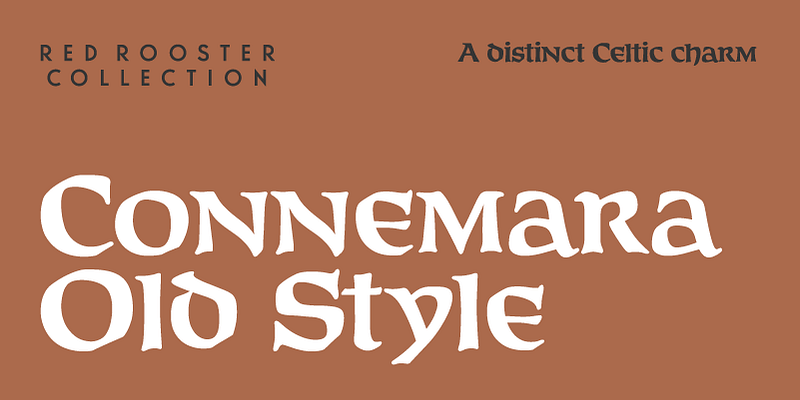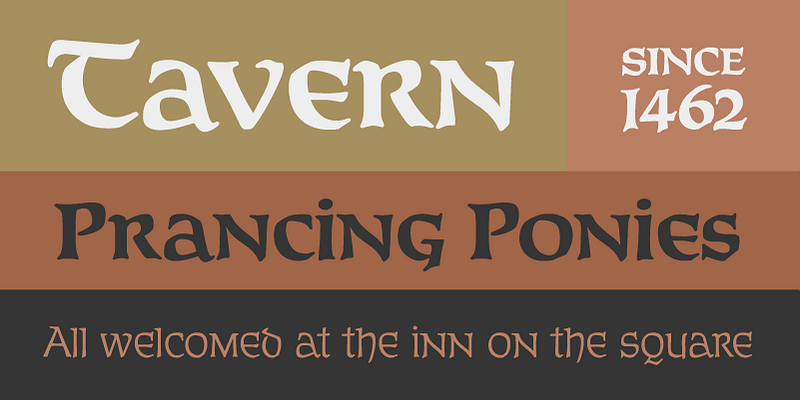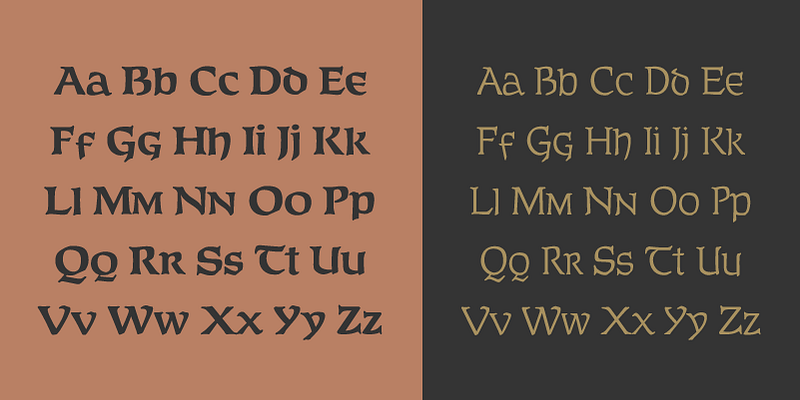
Connemara Old Style est une police onciale qui incarne un charme celtique distinctif. S’inspirant des styles d’écriture irlandais traditionnels avec des formes larges, arrondies et calligraphiques, elle est parfaite pour imiter quelque chose écrit à la plume sur du parchemin ou du vélin. Ce design tout en majuscules est idéal pour donner un aspect historique ou décoratif à des projets tels que des festivals ou des foires, des expositions de musée, des romans fantastiques, des magazines archéologiques, des étiquettes de bières artisanales, des emballages alimentaires artisanaux et des produits faits main.